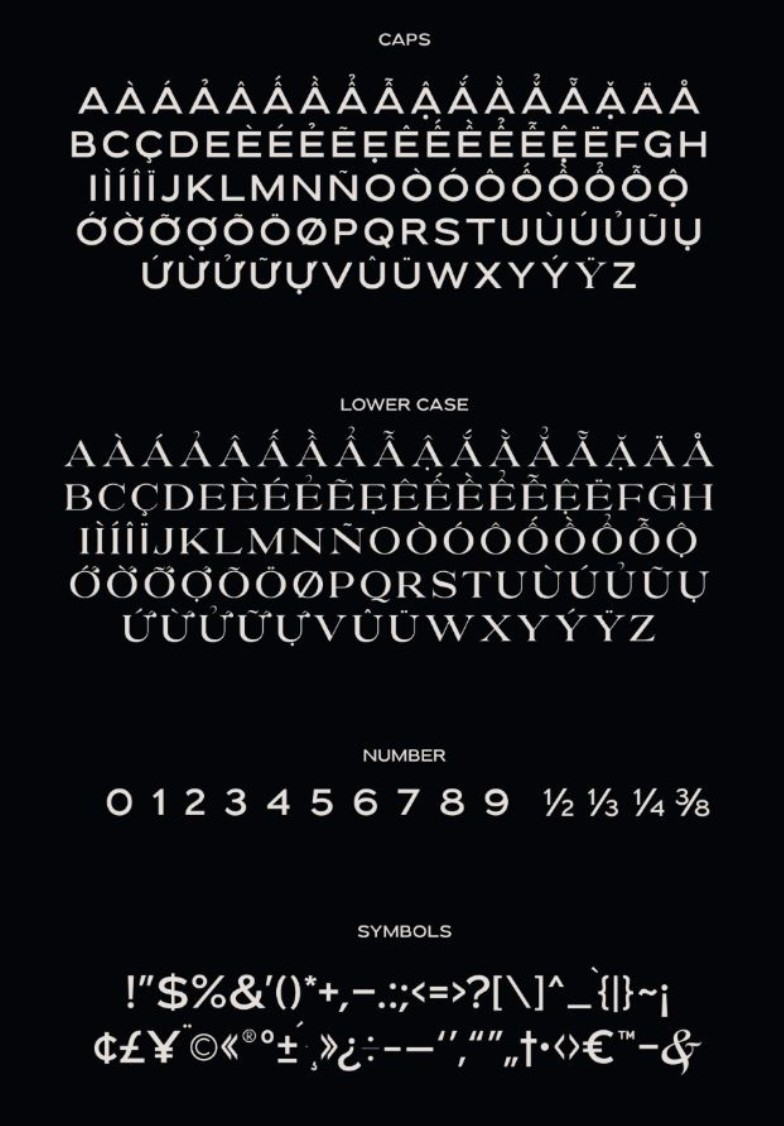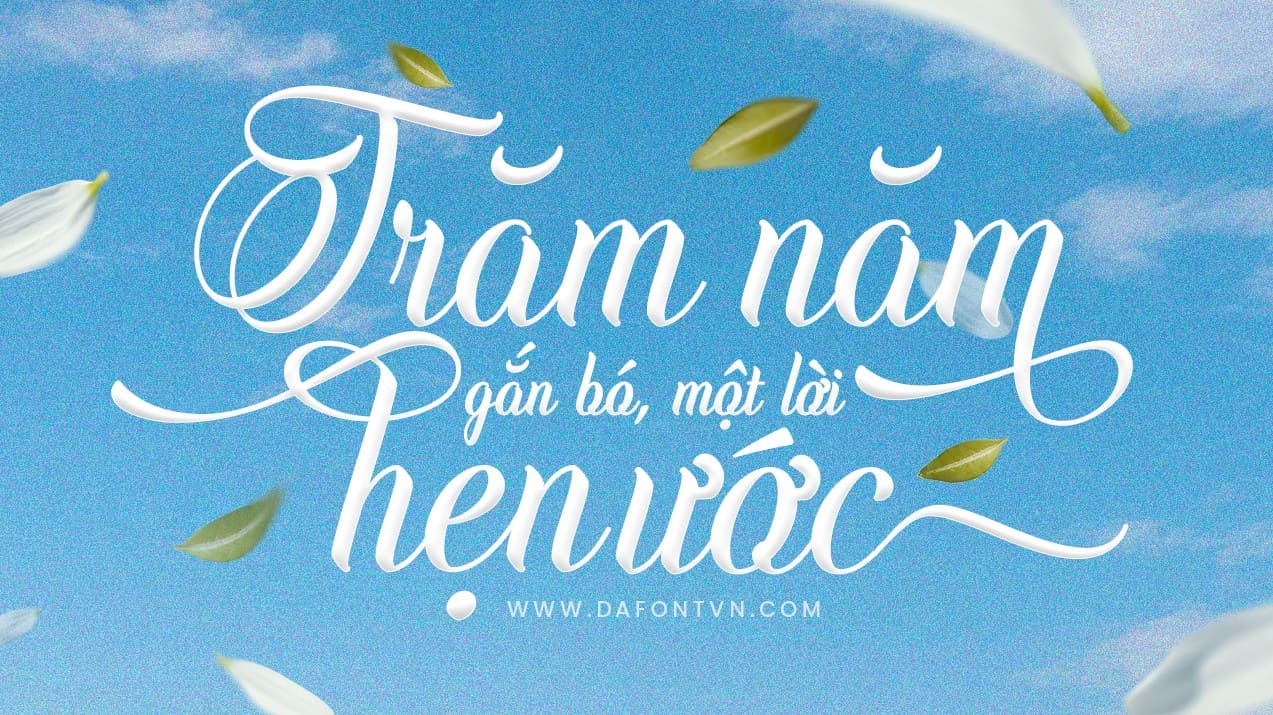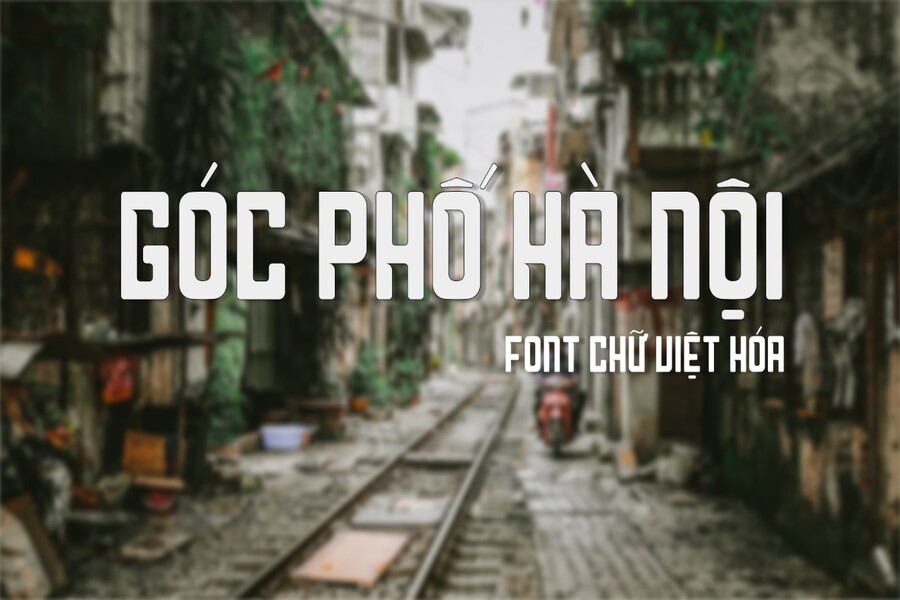
Lỗi Font Việt Hóa Khi Thiết Kế Và Cách Xử Lý Hiệu Quả Cho Designer
Khám phá lý do thật sự khiến font Việt hóa thường gặp lỗi trong Photoshop, Canva, AI hoặc web. Phân tích từng nguyên nhân từ kỹ thuật đến chất lượng Việt hóa. Giúp bạn lựa chọn font phù hợp và tránh rủi ro.
Trong lĩnh vực thiết kế đồ họa tại Việt Nam, việc sử dụng font Việt hóa đã trở thành một phần không thể thiếu. Sự phát triển mạnh mẽ của thiết kế nhận diện thương hiệu, thiết kế truyền thông, typography sáng tạo và đặc biệt là nhu cầu nâng cao chất lượng nội dung số khiến các bộ font quốc tế gốc không còn đủ để đáp ứng hoàn toàn nhu cầu sử dụng. Các nhà thiết kế vì thế tìm đến font Việt hóa như một giải pháp vừa đảm bảo tính thẩm mỹ, vừa hỗ trợ tiếng Việt có dấu đầy đủ. Tuy nhiên, song song với sự phổ biến mạnh mẽ ấy là hàng loạt vấn đề thường gặp khiến không ít người mới lẫn người làm nghề lâu năm cảm thấy phiền toái. Lỗi dấu, lỗi nhảy font, lỗi PDF, lỗi kerning hay các font thư pháp bị “bay dấu” đều là những vấn đề quen thuộc. Nếu không xử lý đúng cách, những lỗi này có thể làm hỏng bố cục, phá vỡ thông điệp thị giác và ảnh hưởng trực tiếp đến chất lượng sản phẩm cuối cùng. Bài viết này sẽ phân tích chi tiết những vấn đề phổ biến nhất khi sử dụng font Việt hóa và hướng dẫn cách khắc phục một cách bài bản, để bất kỳ nhà thiết kế nào cũng có thể tự tin sử dụng font Việt hóa như một công cụ chuyên nghiệp trong quy trình thiết kế của mình.
1. Font Việt Hóa Là Gì? Vì Sao Ngày Càng Được Ưa Chuộng?
Font Việt hóa là những bộ font quốc tế được chỉnh sửa để hỗ trợ đầy đủ tiếng Việt có dấu. Điều này bao gồm bổ sung hoặc chỉnh sửa các ký tự như ă, â, ê, ô, ơ, ư, đ và sáu dấu thanh. Quá trình Việt hóa có thể đòi hỏi nhiều công đoạn phức tạp như bổ sung glyph, tinh chỉnh kerning, cân chỉnh độ cao ký tự, đồng nhất nét stroke và tối ưu khoảng cách để đảm bảo font vừa đẹp vừa dễ đọc khi áp dụng cho ngôn ngữ tiếng Việt.
Tiếng Việt là một trong những ngôn ngữ có hệ thống dấu phức tạp nhất thế giới, do đó nhiều font quốc tế không có sẵn hỗ trợ đầy đủ. Khi sử dụng font gốc để gõ tiếng Việt, người dùng sẽ gặp tình trạng thiếu dấu, ký tự lỗi hoặc chữ hiển thị không đúng vị trí. Vì vậy, font Việt hóa đóng vai trò như một giải pháp hoàn hảo, giúp người dùng có thể tận dụng được vẻ đẹp nguyên bản của font quốc tế mà vẫn đảm bảo hiển thị chính xác tiếng Việt.
Xu hướng sử dụng font Việt hóa ngày càng tăng nhanh nhờ sự bùng nổ của thiết kế số, truyền thông xã hội và thương hiệu Việt Nam. Trong lĩnh vực branding, sự nhất quán về font chữ là yếu tố quan trọng để xây dựng nhận diện thương hiệu. Một bộ font vừa đẹp vừa hỗ trợ đầy đủ tiếng Việt sẽ giúp doanh nghiệp duy trì sự đồng bộ trong mọi ấn phẩm truyền thông, từ logo, brochure đến website. Trong lĩnh vực thiết kế nội dung số, việc dùng font Việt hóa giúp tăng khả năng đọc, giữ tính thẩm mỹ và giảm lỗi khi xuất các định dạng khác nhau.
Ngoài ra, các nhà Việt hóa Việt Nam ngày càng chuyên nghiệp, với những bộ font được chỉnh sửa kỹ lưỡng, thậm chí nâng cấp đẹp hơn cả bản gốc. Điều đó mở ra kho font Việt hóa đa dạng, từ đơn giản, hiện đại đến nghệ thuật, thư pháp, cổ điển, tạo điều kiện cho designer sáng tạo mà không lo bị hạn chế bởi ngôn ngữ.
2. Những Vấn Đề Phổ Biến Khi Dùng Font Việt Hóa Trong Thiết Kế
Mặc dù mang lại nhiều lợi ích, font Việt hóa cũng là nguyên nhân của hàng loạt rắc rối khi sử dụng không đúng cách. Dưới đây là các vấn đề phổ biến mà designer thường gặp.
2.1. Lỗi không hiển thị dấu tiếng Việt
Đây là lỗi phổ biến nhất và cũng gây bối rối nhất. Người dùng tải font về, gõ tiếng Việt nhưng chữ bị lỗi hoặc không có dấu. Thậm chí một số ứng dụng hiển thị đúng trong phần mềm thiết kế nhưng khi xuất ra lại bị sai hoàn toàn.
Phần lớn nguyên nhân xuất phát từ việc font chưa được Việt hóa chuẩn. Có những bộ font được Việt hóa sơ sài, chỉ thêm một vài ký tự cơ bản mà không hoàn chỉnh bảng Unicode. Một số bộ bị lỗi encoding trong quá trình chuyển đổi khiến phần mềm không thể nhận diện đúng ký tự.
Nếu bạn gõ tiếng Việt bằng Unicode nhưng font chỉ hỗ trợ VNI hoặc TCVN3, lỗi cũng sẽ xuất hiện ngay lập tức. Tình trạng này xảy ra rất nhiều đối với những người dùng font miễn phí trên mạng mà không kiểm tra nguồn gốc.
Giải pháp hiệu quả nhất là chỉ sử dụng font từ nguồn uy tín, kiểm tra bảng glyph trước khi dùng và tránh lấy font trôi nổi trên mạng. Người dùng nên thử gõ các từ chứa nhiều dấu phức tạp như “nghiêng ngả”, “kỹ thuật”, “thẩm mỹ”, “tự do” để đảm bảo font hoạt động ổn định.
2.2. Font Việt hóa bị lỗi khi xuất PDF
Ngay cả những designer dày dạn kinh nghiệm cũng từng gặp ác mộng khi xuất file PDF và nhận ra toàn bộ chữ biến thành ô vuông hoặc bị vỡ nét. Font Việt hóa khi xuất PDF thường gặp hai vấn đề chính: hệ thống không thể nhúng font vào file hoặc font không tương thích trong quá trình render PDF.
Một số font Việt hóa được chỉnh sửa thủ công không đảm bảo cấu trúc kỹ thuật theo chuẩn PostScript hoặc OpenType khiến phần mềm không thể nhúng font đúng cách. Trong khi đó, các phần mềm như Adobe Illustrator, InDesign hay CorelDRAW đều yêu cầu hệ thống font đạt chuẩn để hỗ trợ PDF đầy đủ.
Giải pháp phổ biến nhất để tránh lỗi này là bật chế độ nhúng font khi xuất PDF hoặc chuyển text sang outline. Dù vậy, phương pháp outline cần sử dụng đúng thời điểm vì nó biến chữ thành vector, không thể chỉnh sửa lại nội dung.
2.3. Font thư pháp hiển thị sai khi gõ dấu
Font thư pháp là nhóm font gây vấn đề nhiều nhất vì các bộ font này được thiết kế với vận nét uốn lượn, cấu trúc phức tạp và nhiều biến thể stroke. Khi thêm dấu tiếng Việt, đặc biệt ở các ký tự như “ễ”, “ỗ”, “ũ”, dấu dễ bị lệch hoặc trùng vào nét chữ.